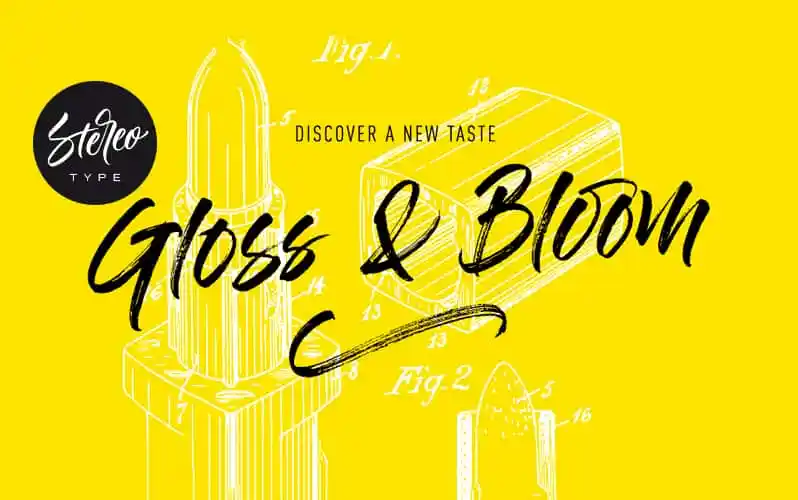
Gloss And Bloom Font – Download Grátis
Gloss And Bloom é uma tipografia script que surge da arte de escrita de Sean Delloro. Este tipo foi criado para aqueles buscando uma caligrafia robusta e sofisticada. Inspirado nas obras de Delloro, Gloss And Bloom oferece uma variedade completa de letras alternativas, sublinhados e deslizamentos que adicionam profundidade e interesse à qualquer projeto. Com a sua consistente elegância misturada com um toque de rusticidade, esta fonte é ideal para designers que valorizam tanto o detalhe quanto a personalização. Seja para uso em branding, design editorial ou até mesmo gráficos de arte digital, Gloss And Bloom traz uma aposta certa e moderna à sua paleta de recursos visuais. Sem dúvida um ativo valioso para qualquer designer buscando expressar elegância e versatilidade através da escrita digital.